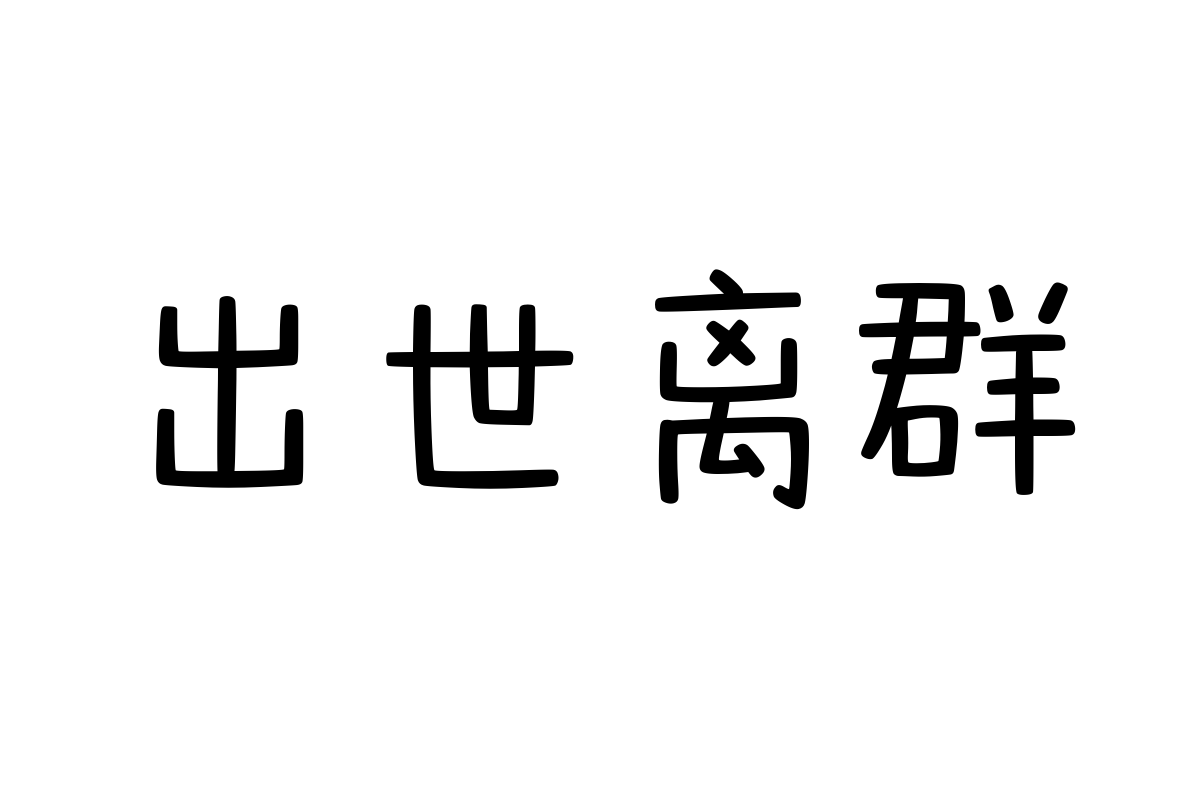
汉仪天真体是一款具有独特风格的中文字体。它由汉仪字库倾心打造,旨在为设计师和艺术家提供一种既简洁又富有表现力的字体选择。这款字体以其独特的风格和特点吸引了众多用户的关注。
汉仪天真体的字形结构紧凑而不失灵动,笔画流畅且富有变化。它的每个字母都经过精心设计,使得整体视觉效果更加和谐统一。同时,汉仪天真体还注重细节的处理,无论是字母之间的间距还是整体的排版效果都展现出了其独特的魅力。
此外,汉仪天真体还具备多种应用场景。它可以用于各种类型的文本设计,如标题、正文、广告等。无论是在网页设计、海报制作还是其他视觉作品中,汉仪天真体都能为作品增添一份独特的韵味。